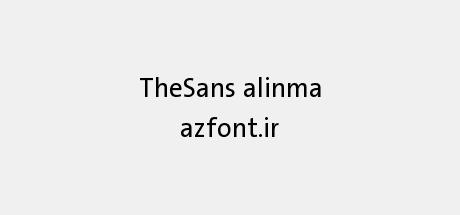
TheSans alinma
قلم زیبای TheSans Plain از سری قلم های بسیار زیبا برای تایپوگرافی و لوگو تایپ می باشد.این قلم در وزن Plain و توسط Steven Snape http://communities.msn.com/solidsnakesgameshrine طراحی و منتشر شده است.